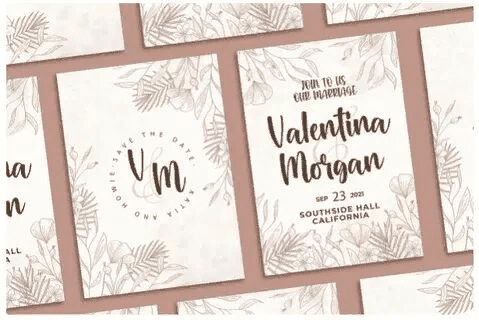
Название: Raverdia Modern Script Font (2021)
Представляем вам наш новый продукт - современный шрифт Raverdia.
Шрифт Raverdia вдохновлен стилем задорной каллиграфии с веселой темой, очень хорошо подходит для логотипа, детского плаката, флаера, детской книги, мультфильма, комикса и т.д.
ОСОБЕННОСТИ :
Прописные
Строчные
Число
Пунктуация
Многоязычный